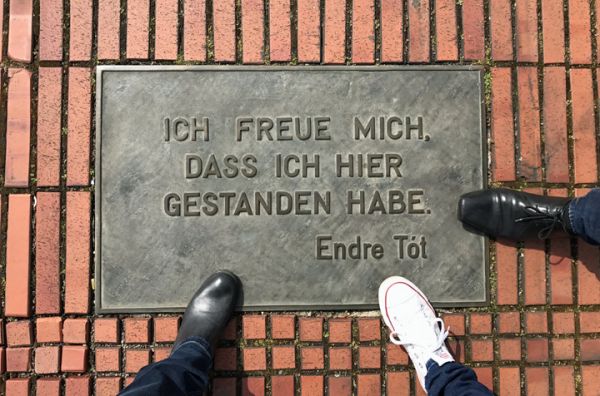
Schrift auf Steinplatte in Köln gesucht
ich suche den Namen der Schrift auf folgender Steinplatte im Kölner Museum Ludwig:
Dachte erst, es wäre die Aaux, aber es scheint doch ein paar Unterschiede zu geben (insbesondere beim A, E und C).
I am glad that I have stood here” – this was inscribed in Hungarian on his bronze plaque placed in the pavement in 1998 in front of Artpool's art space in Budapest (60, Paulay Ede St.). Six years later a similarly inscribed plaque („Ich freue mich, dass ich hier gestanden habe”) was placed in the floor of the roof terrace of the Cologne Ludwig Museum.